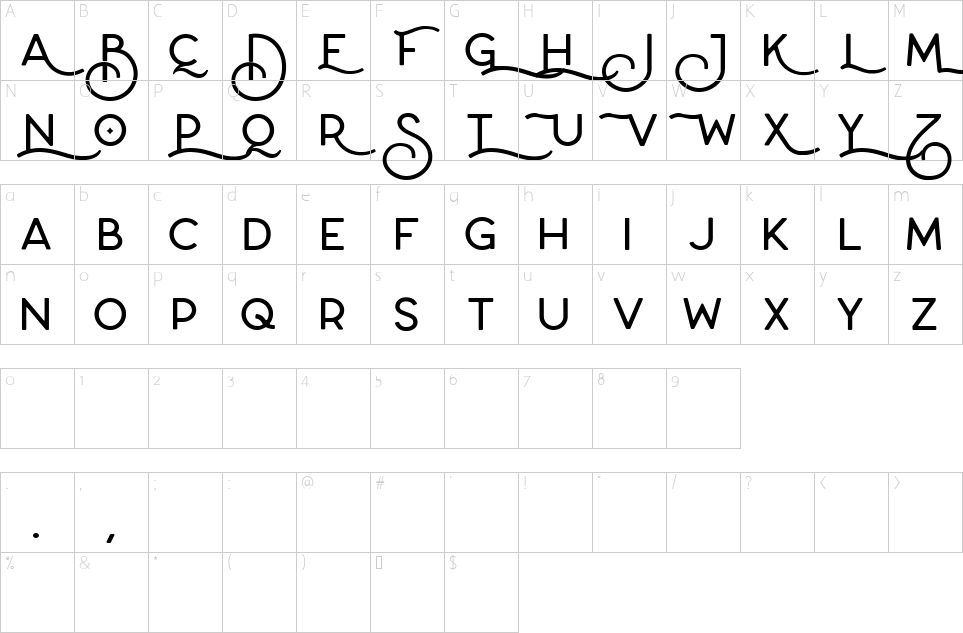
A fonte Aorell é uma elegante escolha para qualquer projeto de design gráfico, seja para criar títulos impactantes ou texto em formato de corpo. Ela foi cuidadosamente projetada pela equipe do Metafontsy, que tem um histórico em desenvolver fontes de alta qualidade. Aarell foi adotada por desbravadores de projetos web e designers gráficos em todo o mundo, acreditando que seu estilo sofisticado e fluido traz um toque único aos seus designs. Desde sua disponibilização, Aorell foi baixada mais de 4.799 vezes, demonstrando seu valor e aprimorando a experiência visual de quem a usa. Com seu design detalhado e versátil, é perfeita para incorporar em diversos ambientes digitais, garantindo que seu projeto se destaque em meio ao excesso de conteúdo online.